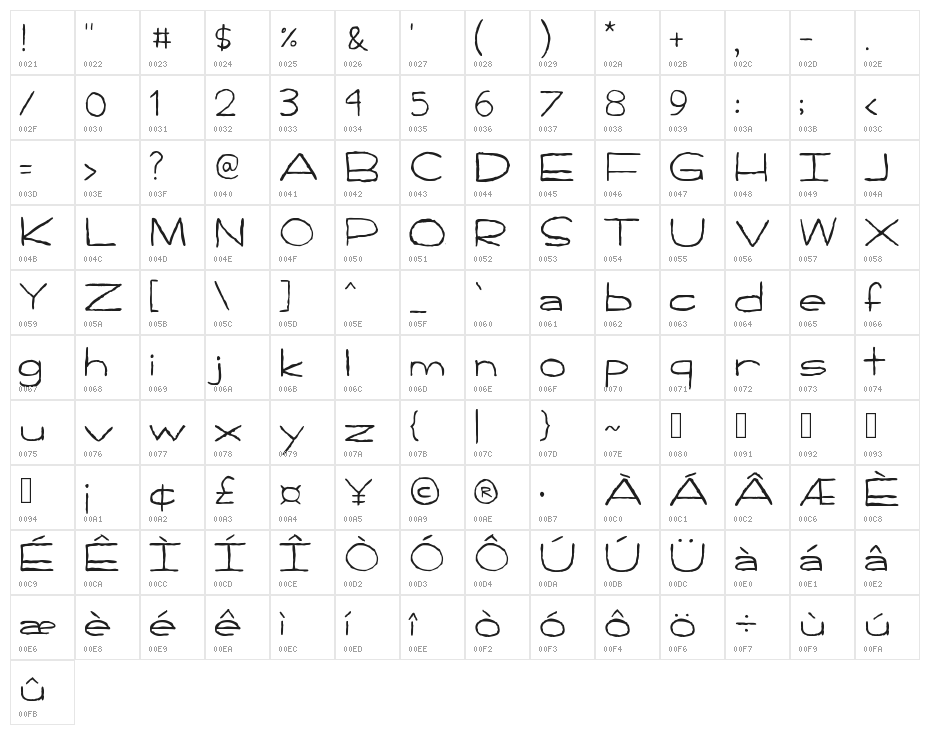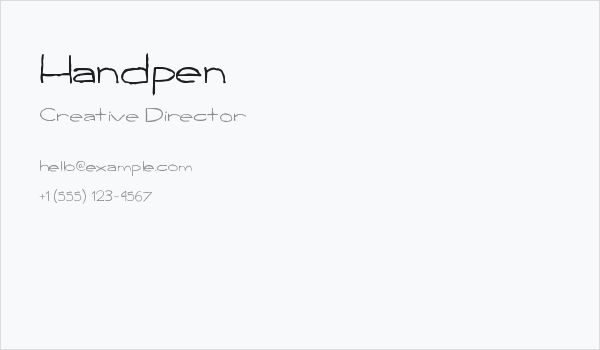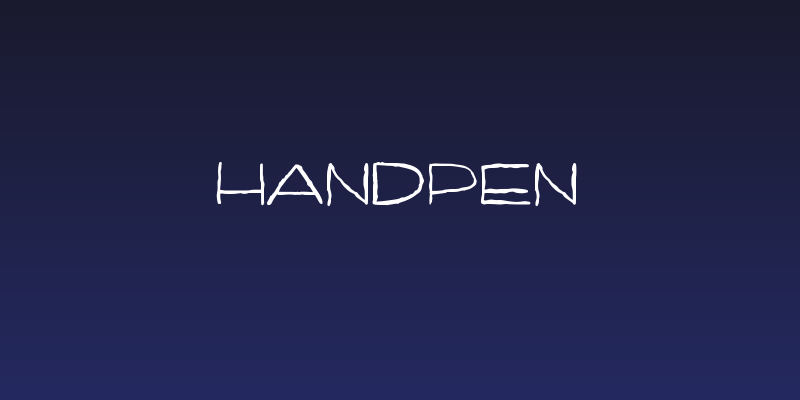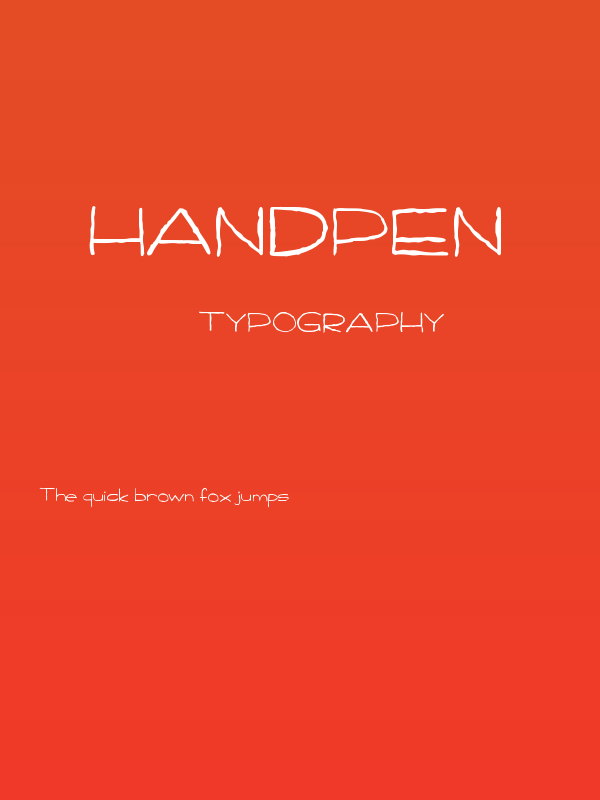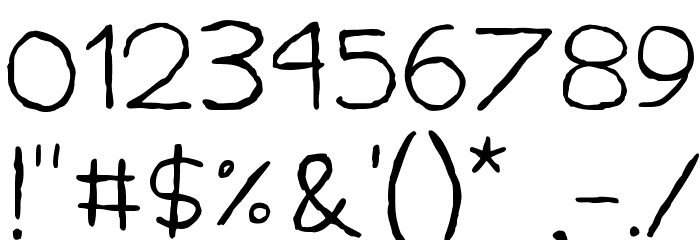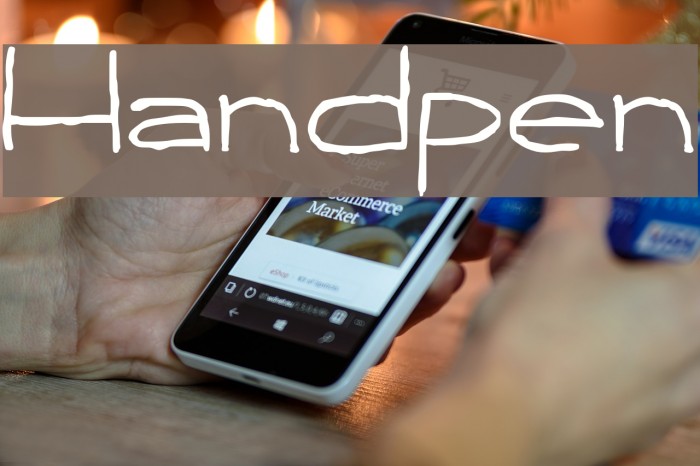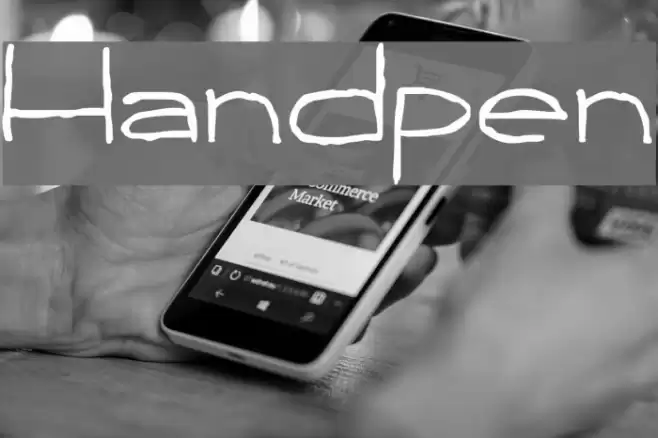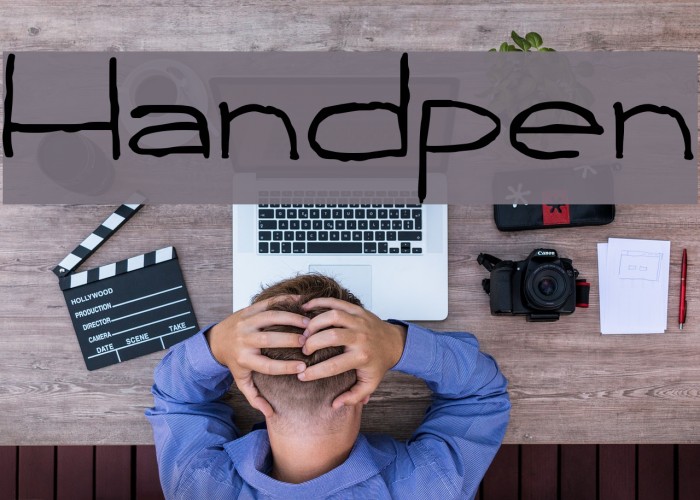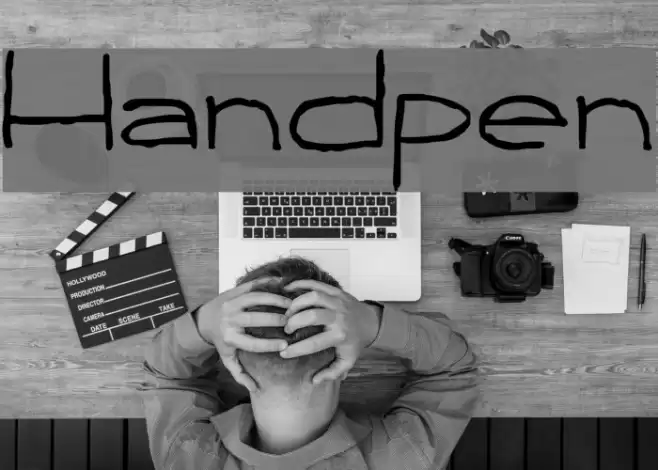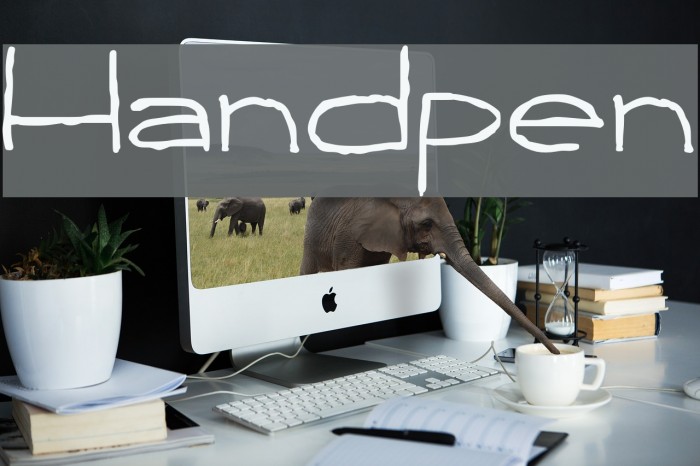
Handpen Font
| Gesamtstil | Casual, Playful |
| Anwendungsfall | Logos, Invitations, Greeting Cards |
| Vorgeschlagene Projekte | Ideal for greeting cards, invitations, personal branding, and creative projects that require a personal touch. |